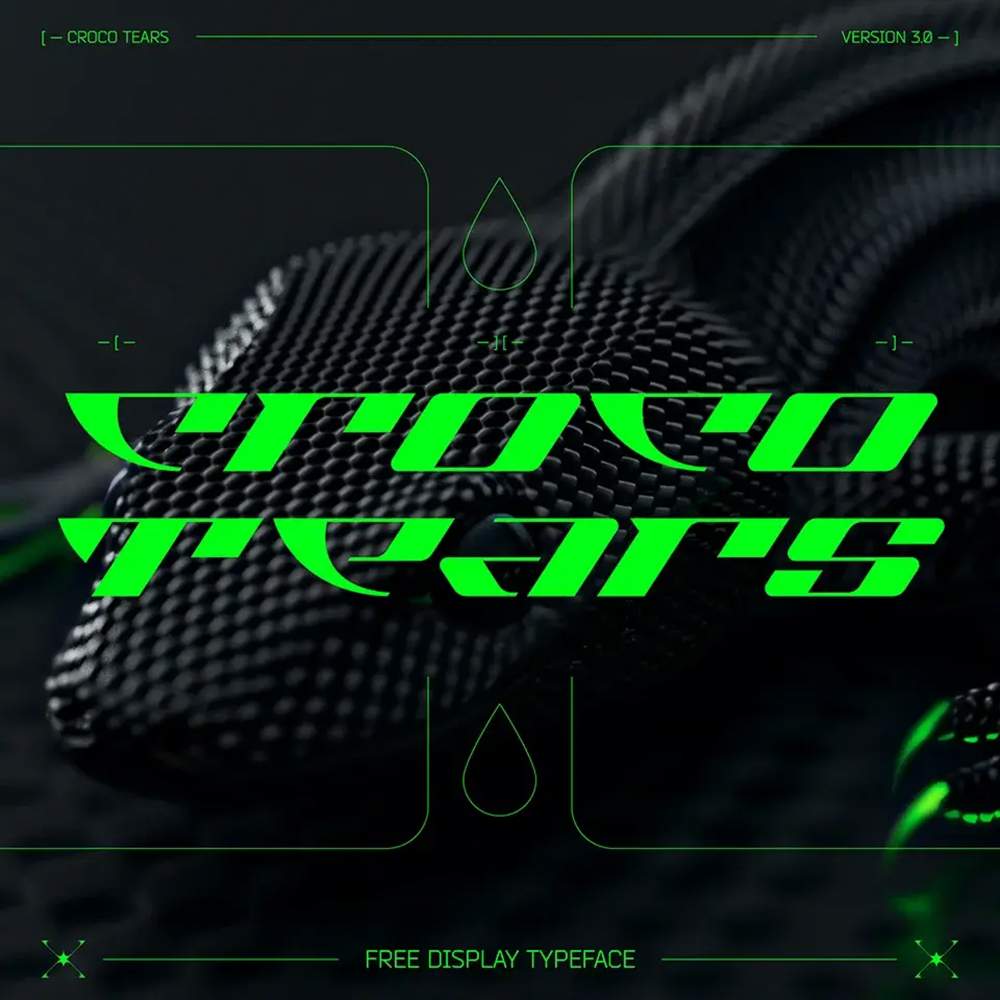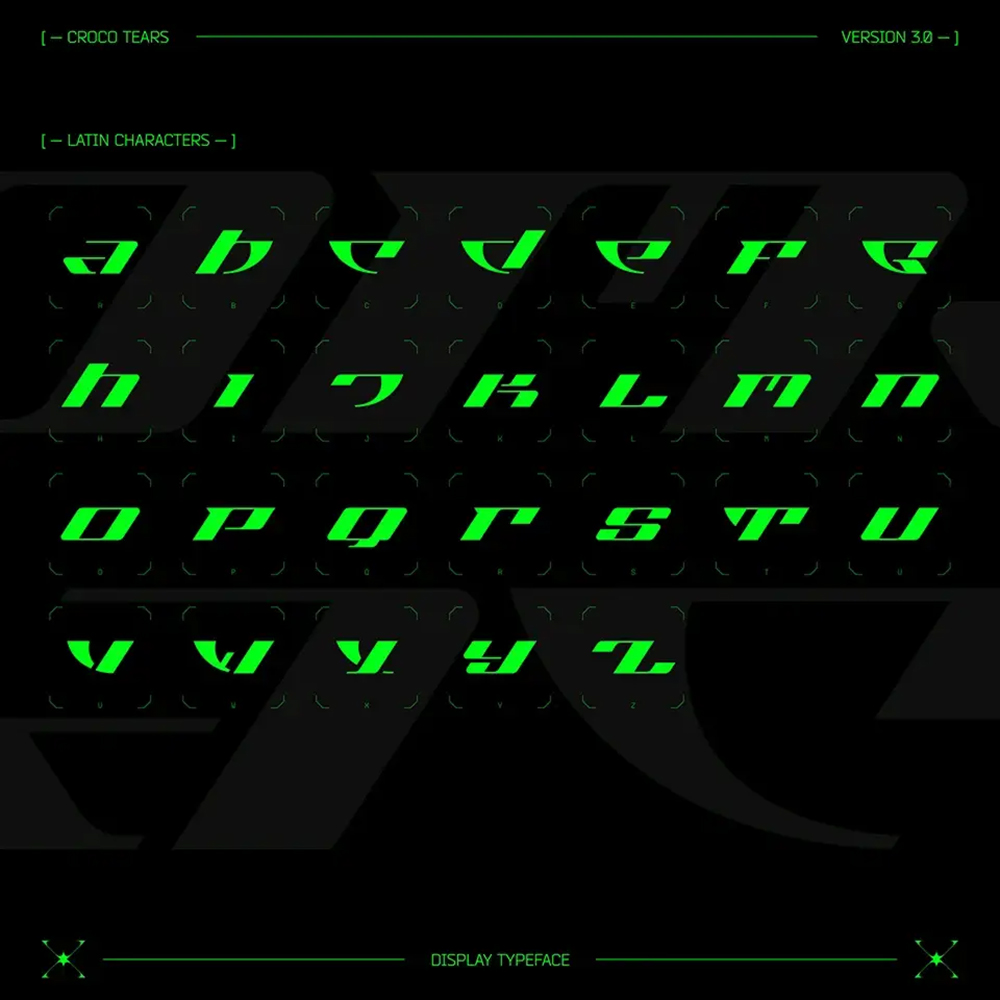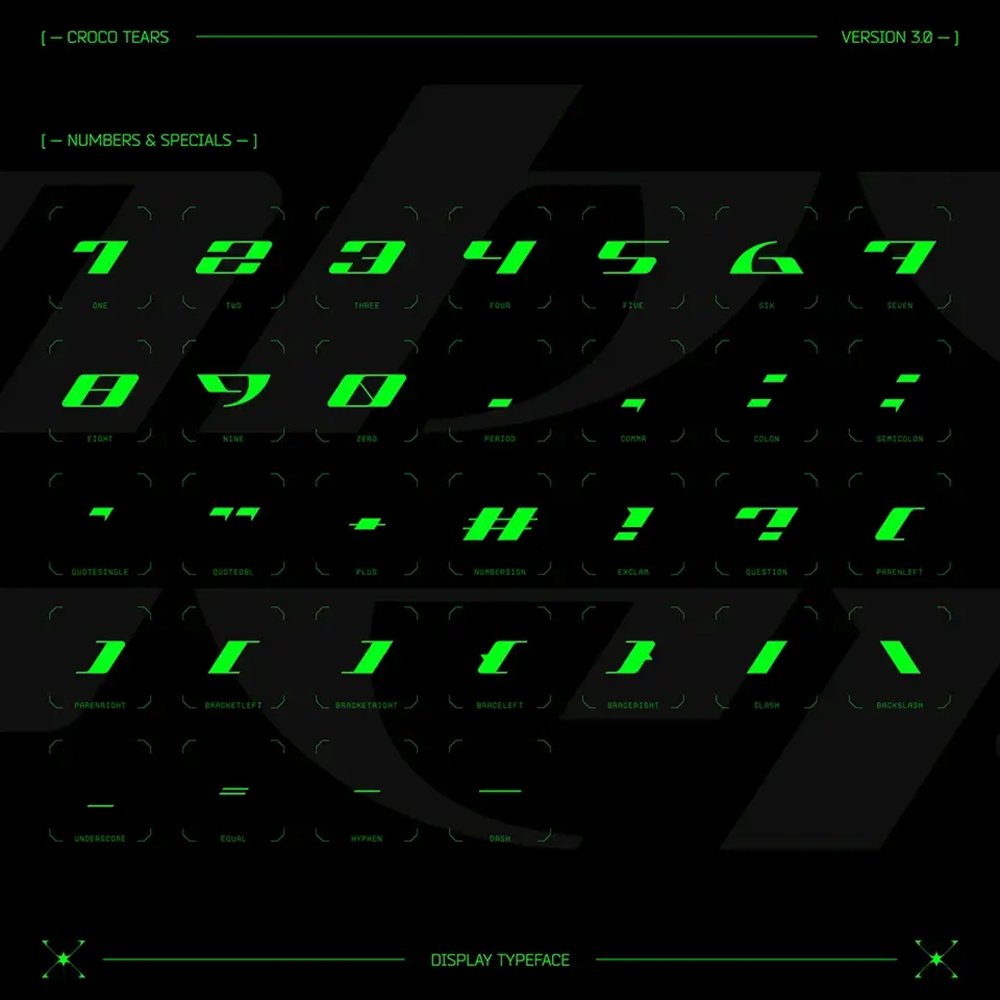
دانلود فونت انگلیسی Croco Tears Font
فونت پرمیوم و انگلیسی Croco Tears Font یک فونت نمایشی است که زیباییشناسی ورزشی را با لحنی تهاجمی و خزنده ترکیب میکند و فونتی جسورانه و چشمنواز…
فونت پرمیوم و انگلیسی Croco Tears Font یک فونت نمایشی است که زیباییشناسی ورزشی را با لحنی تهاجمی و خزنده ترکیب میکند و فونتی جسورانه و چشمنواز ایجاد میکند که برای لوگوها، عناوین و طرحهای لباس ایدهآل است. این فونت شامل کاراکترهای لاتین و سیریلیک است و با ترکیب منحصر به فردش از عناصر ورزشی و خزنده، آن را در هر پروژه طراحی متمایز میکند. سبک قدرتمند و متمایز آن میتواند تأثیر بصری قوی به کار شما اضافه کند، چه برای لوگو، تیتر یا لباس استفاده شود. Croco Tears یک فونت همهکاره است که میتوان آن را به راحتی در سبکهای مختلف طراحی، از مدرن و جسورانه گرفته تا ورزشی و خشن گنجاند.